Hoy en día, puedes encontrar una variedad de fuentes para usar en los proyectos que desees, si quieres convertirte en uno de los mejores diseñadores, debes contar con una lista de las tipografías modernas que serán tendencia en el 2022. Así que, sigue bajando y descubre las opciones gratuitas que tenemos para ti; de esta manera, podrás crear encabezados, posters, logotipos y otros trabajos creativos con solo hacer un par de clics.
15 tipografías modernas que todo diseñador gráfico debe conocer
1. Lombok
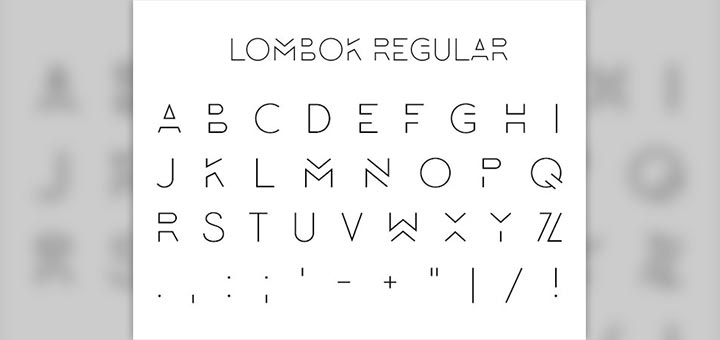
La fuente Lombok es un tipo de letra creada por Alexandre Pietre en el año 2014, es de uso libre y pertenece a las tipografías Sans Serif, lo que quiere decir, que es un trazo limpio que no tiene líneas de proyección ni rizos en los extremos. Además, se destaca por su diseño elegante con elementos geométricos que te parecerán bastante interesantes.
2. One Day
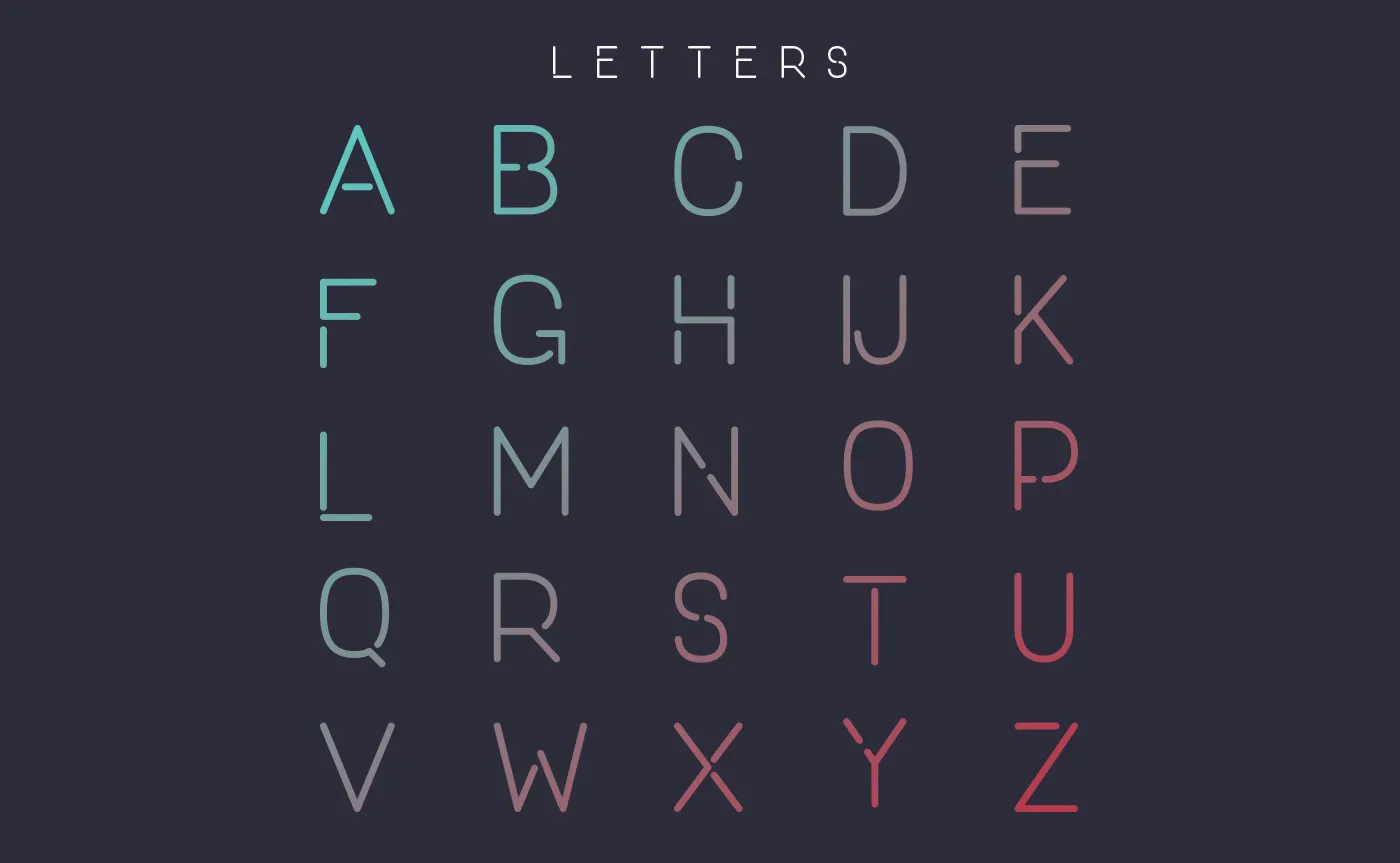
Sorpréndete con la tipografía One Day que sobresale por su estilo en mayúsculas y sus líneas entre cortadas que te ofrecen un estilo futurista e innovador. Fue desarrollada por Nawras Moneer para uso gratuito y personal. Incluye trazos delgados con formas redondas que quedarán bien en cualquier diseño que desees.
3. Aqua
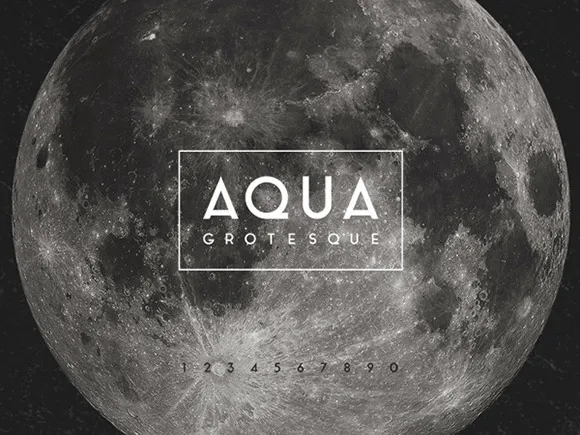
Aqua es una tipografía moderna que no te puedes perder en el 2022, ha sido creada por Laura Pol y tienes la posibilidad de descargarla sin ningún costo. Fue inspirada en los tipos de letras geométricas con ángulos pronunciados y combinaciones de mayúsculas y minúsculas. Es perfecta para encabezados, logotipos y posters que requieran de un estilo atemporal.
4. Polya
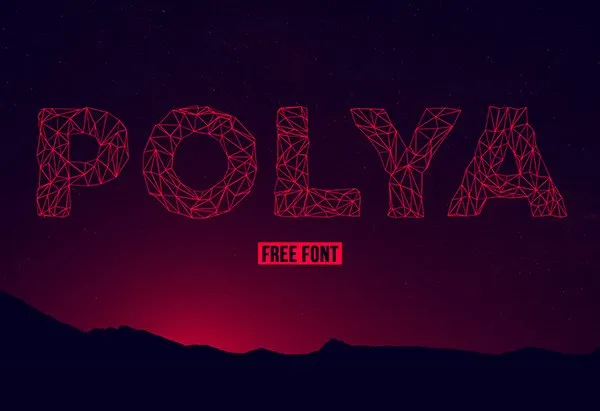
La fuente Polya fue inspirada por Adrien Coquet como una alternativa de uso gratuito para todos los diseñadores que trabajan con los estilos 3D en el modelado por computadora. Esta malla poligonal tiene líneas delgadas y asimétricas que te proporcionan un estilo irregular y llamativo que sin duda deberás usar en tus proyectos.
5. Higher
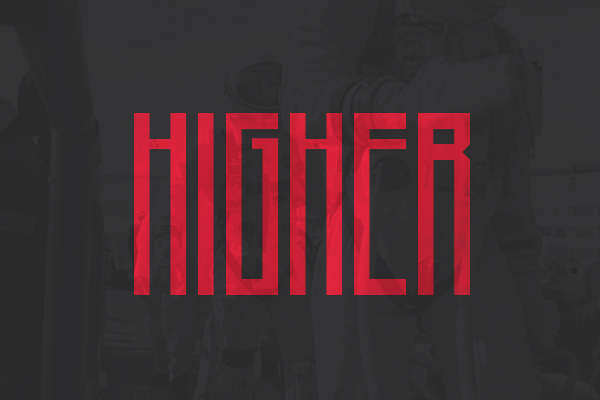
La autora Marisa Passos es la creadora de la tipografía Higher como parte de un proyecto estudiantil y desde entonces se puede encontrar para uso público y sin costo. Tiene un diseño simple y alargado en mayúsculas que se condensan en la parte inferior o superior de las letras, número y demás caracteres.
6. Aroma
Otro de los inventos de Laura Pol es la fuente Aroma que se destaca visualmente por su aspecto robusto y en negrita. También, cuenta con extremos curveados y ángulos marcados que son similares a los tipos de letra de caligrafía. Recuerda que, puedes usarlos en diseños retro o contemporáneos.
7. Minimalust
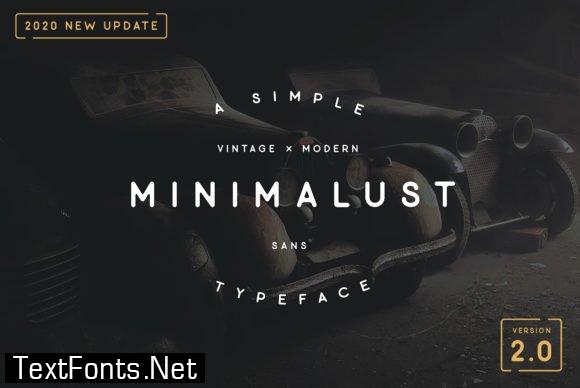
Minimalust es una de las fuentes clásicas que todo diseñador debe usar en sus proyectos, fue creada por Pratama Yudha como un tipo de letra limpio y minimalista que puedes añadir a posters, títulos y revistas formales. Además, hace parte de la tipografía Sans Seriff y es inspirada en la imprenta y la escritura a mano gracias a sus líneas suaves con extremos redondos.
8. Metria
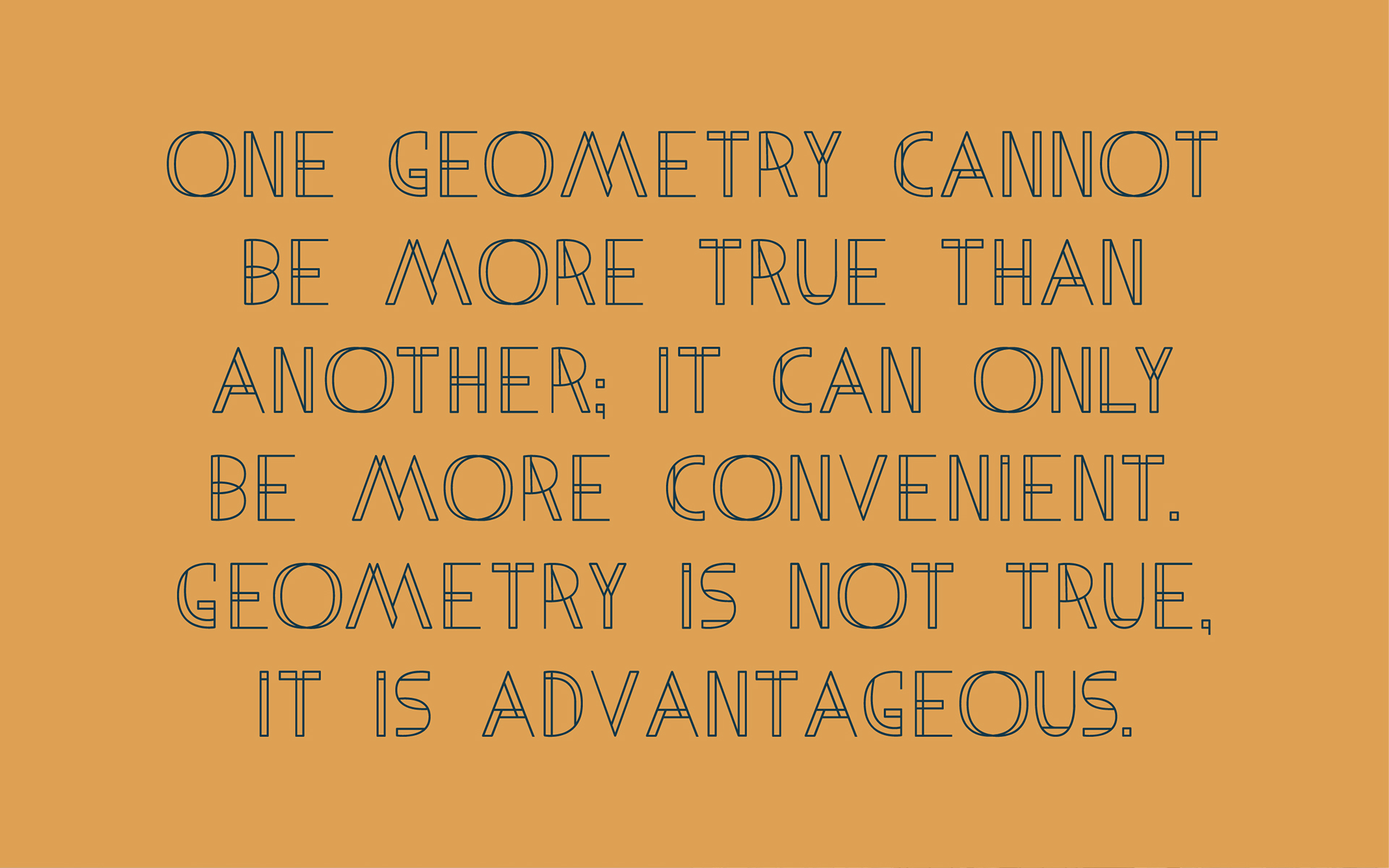
Sin duda, debes añadir a tu lista la innovadora fuente Metria que fue diseñada por Jake Lunde, esta tipografía cuenta con un estilo geométrico y simple que podrás usar de mil formas. Ten presente que, posee una combinación de círculos perfectos con ángulos consistentes y líneas bien definidas que te sorprenderán.
9. Brassie
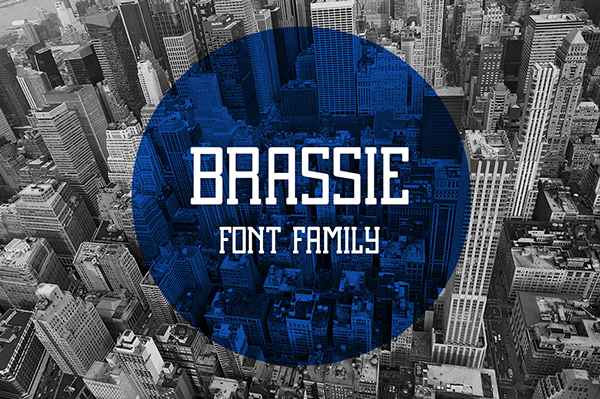
Brassie es una nueva fuente moderna y novedosa que fue diseñada por Ryan Welch, se caracteriza por tener líneas de soporte en la parte interior que le dan un toque particular y único. Esta tipografía de tipo serif cuenta con trazos rectos y robustos que sobresale bastante bien entre tus proyectos.
10. Ministry
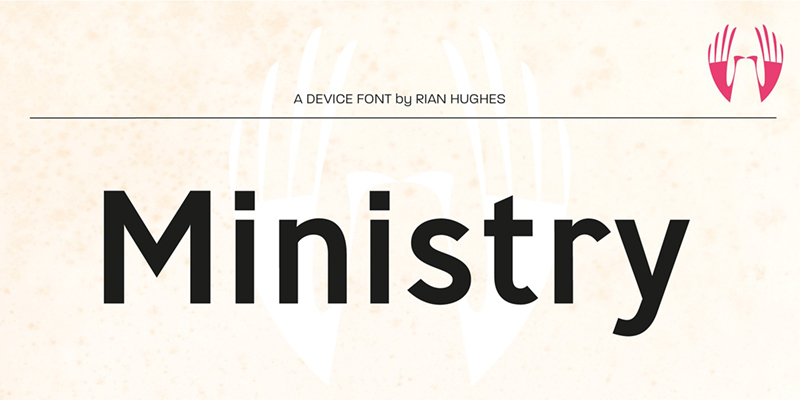
Descarga de forma gratuita la tipografía Ministry que ha sido diseñada por Víctor Tognollo, esta fuente posee ángulos curveados con líneas alargadas y colas condensadas que te proporcionan un estilo interesante. Además, tienen una forma elegante y delicada que se destaca entre la lista de sans serif.
11. Nagasaki
La diseñadora Sasha Lacob ha creado la fuente Nagasaki con un estilo robusto, condensado y en negrita que sin duda impacta a primera vista. Esta tipografía en minúscula cuenta con extremos redondos, alargados y con poco espacio entre cada letra que te permite llamar la atención del lector en segundos.
12. Disclaimer
Disclaimer es una tipografía estrecha y alargada que podrás usar en encabezados y titulares reducidos en donde debes aprovechar el espacio disponible al máximo. Fue diseñada por Font Fabric con un estilo condensado y en negrita que hace lucir a los caracteres más altos e imponentes.
13. Matey
En tu lista de fuentes no puede faltar la tipografía Matey que fue inventada por Andreas Leonidou, se destaca por tener un diseño clásico sin dejar de ser moderna y con un toque contemporáneo. También, sobresale por sus curvas geométricas que logran causar gran impacto en logotipos, títulos o encabezados.